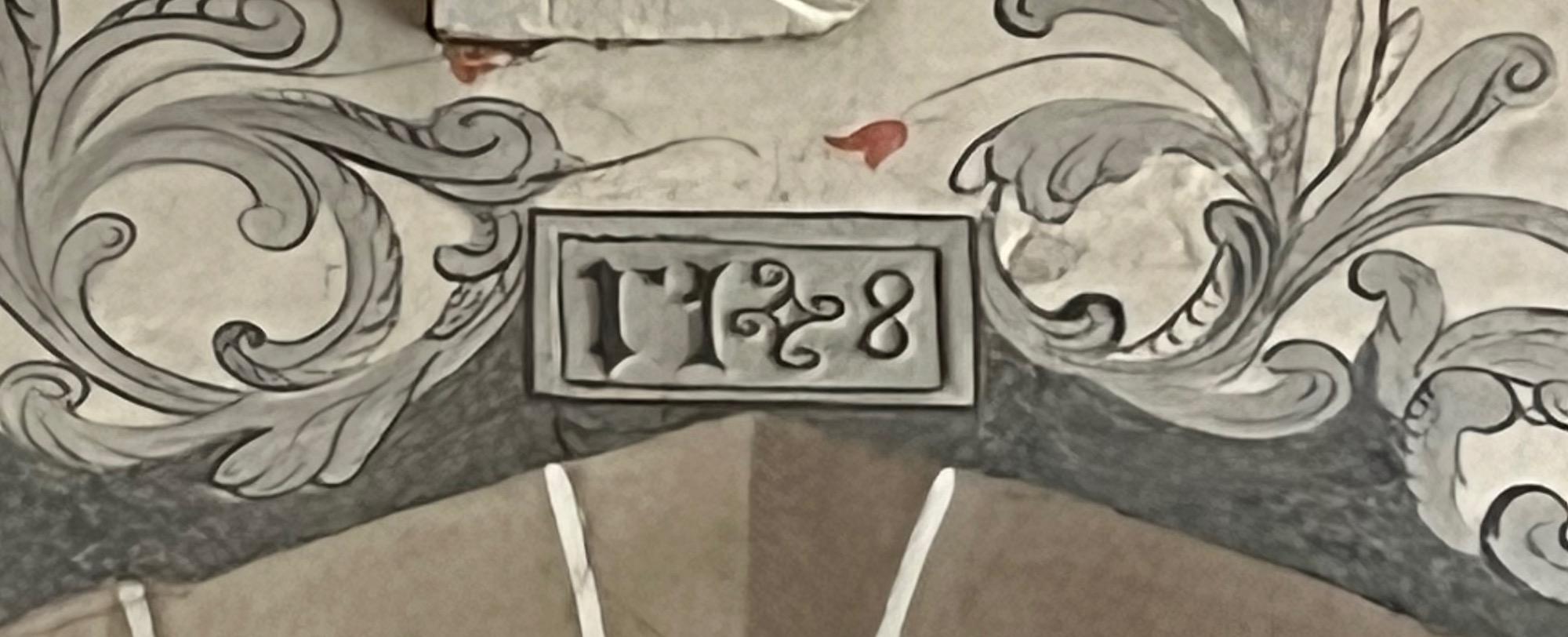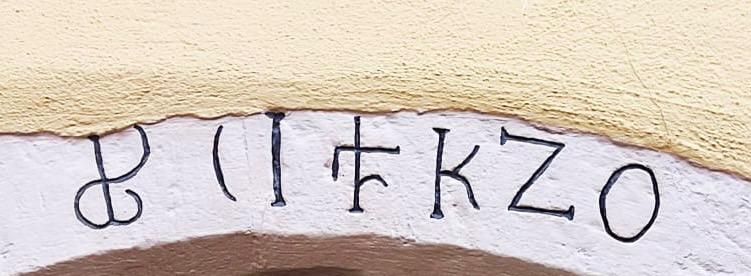
Suche die Sprache beigefügten Schriftzugs über Hauseingang im Elsass
Bei einem Spaziergang in Egisheim, im Elsass, sah ich über einem Hauseingang diesen Schriftzug. Ich habe sämtliche Alphabete durchsucht, jedoch nichts passendes gefunden… Manche Schriftzeichen sehen bekannt aus (o,k,z) andere weniger… Oder ist es möglich, dass das eine bestimmte Form der Kalligrafie oder einfach Fantasiesprache ist?
Das sind keine Runen.
Das erste Zeichen links ist eine Ziffer 1. Das Zeichen in der Mitte (zwischen I und K) ist eine Hausmarke. Bei ›Z O‹ könnte es sich um die Ziffern 2 0 handeln. Die ›Klammer‹ ( könnte ursprünglich eine Ziffer 7 gewesen sein, bei der Überpinselung mißverstanden.
die schreibweise von zahlen war ja früher durchaus spannend. ich hab dieses bild in einer kirche (dörnberg in hessen) gemacht und auch lang gerätselt welches jahr das sein soll. ich bin mittlerweile für 1748.
also – wenn ich dich richtig verstehe –
jahreszahl 1720
initialen IK
und in der mitte das hauszeichen?
vermutlich ja. Die Form  (  kann ich mir nicht anders erklären.
Die 1 ist eine geschwänzte 1. Gibt es häufig bei Inschriften.